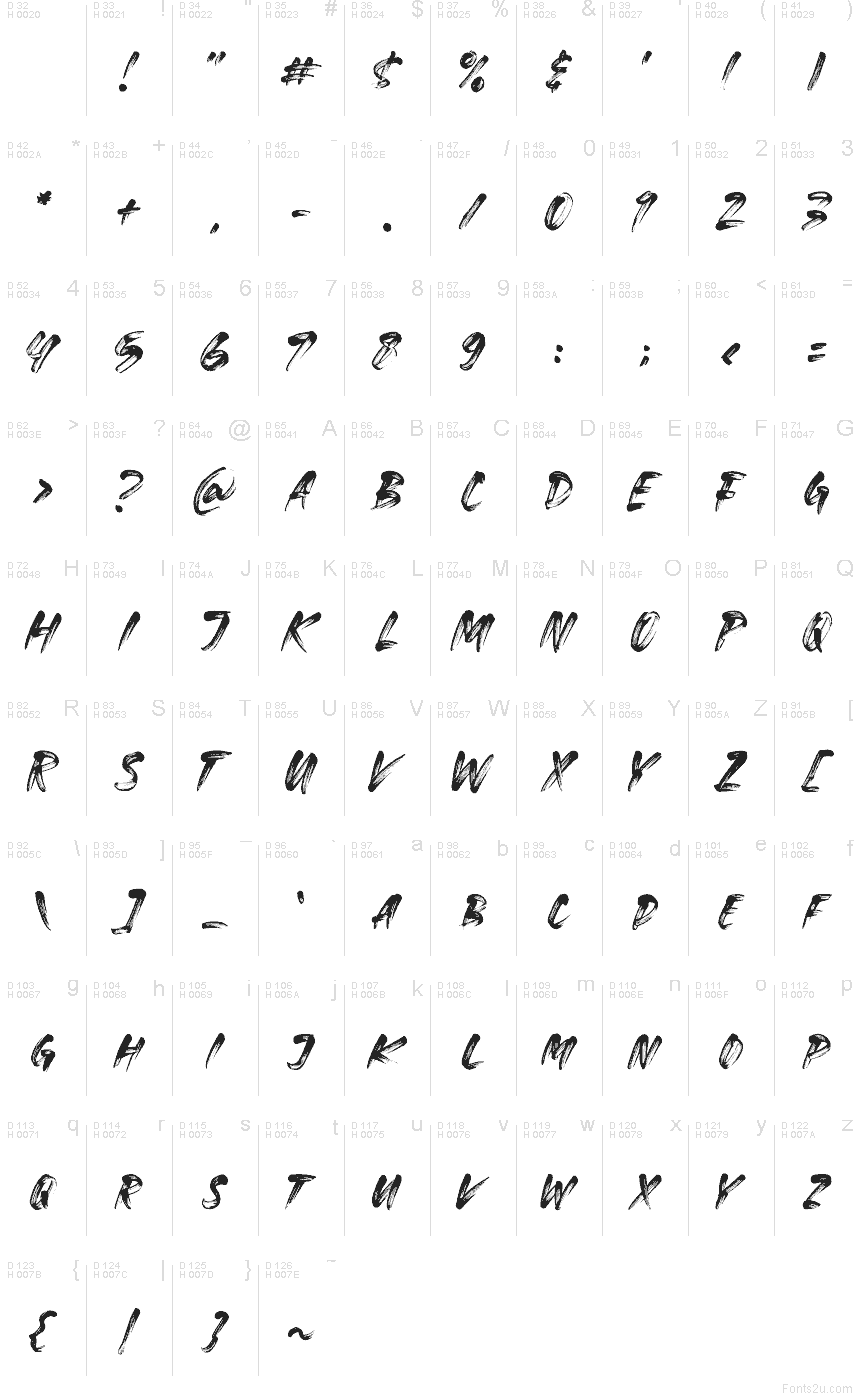
Aversa Vector от Graphicfresh Corporation — это бесплатный акцидентный шрифт в стиле «сухой кисти» с динамичным, по-настоящему живым характером. Буквы наклоняются и «метут» пространство широкими мазками, с рваными краями и полосчатой текстурой. Это придает заглавным буквам непринужденный, плакатный вид — никакой стерильной «вылизанности», только драйв ручной работы.
Шрифт идеально впишется в оформление музыкальных релизов, стритвир-дизайны, афиши мероприятий, обложки журналов и заголовки, где сырой малярный мазок смотрится уместнее, чем рафинированный леттеринг. Поскольку это бесплатный шрифт, он также отлично подходит для короткого брендинга, промо в соцсетях и монограмм: текстура кисти создает достаточно движения, чтобы даже пара букв выглядела энергично.